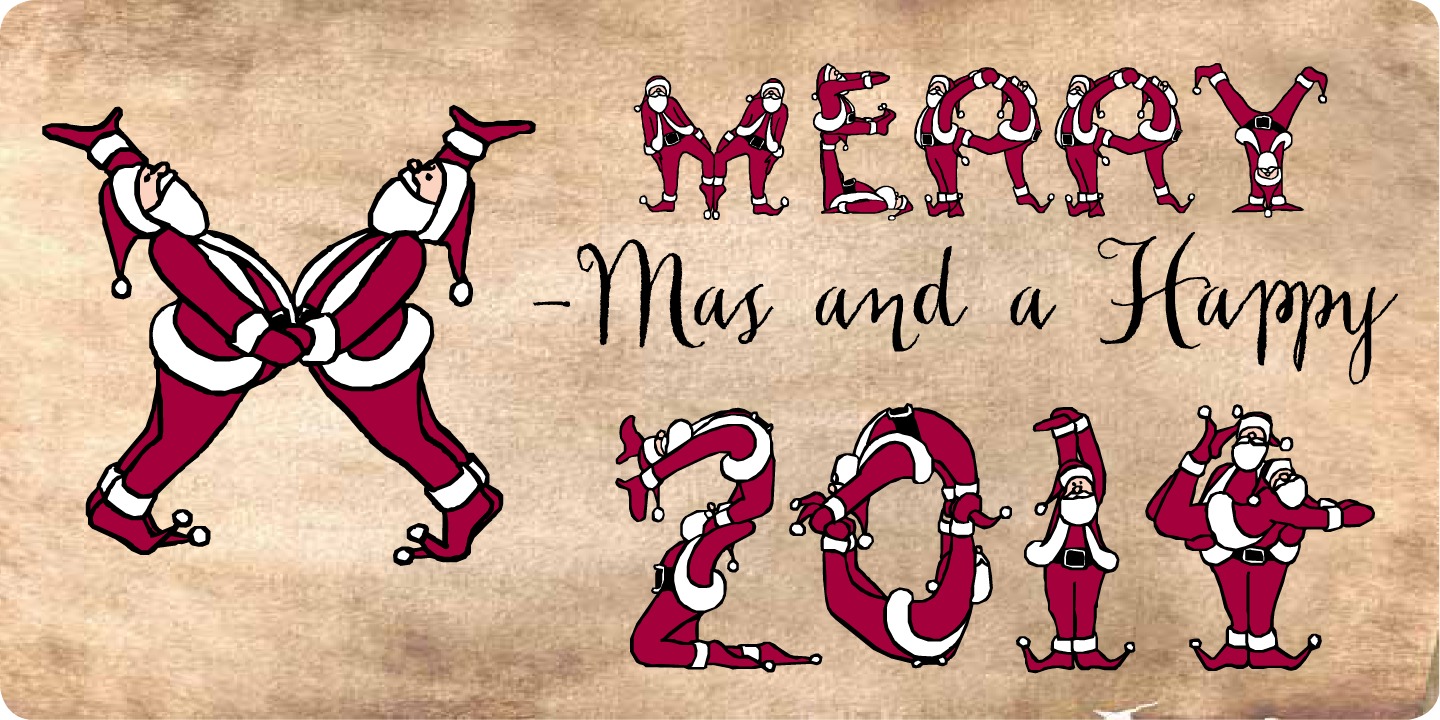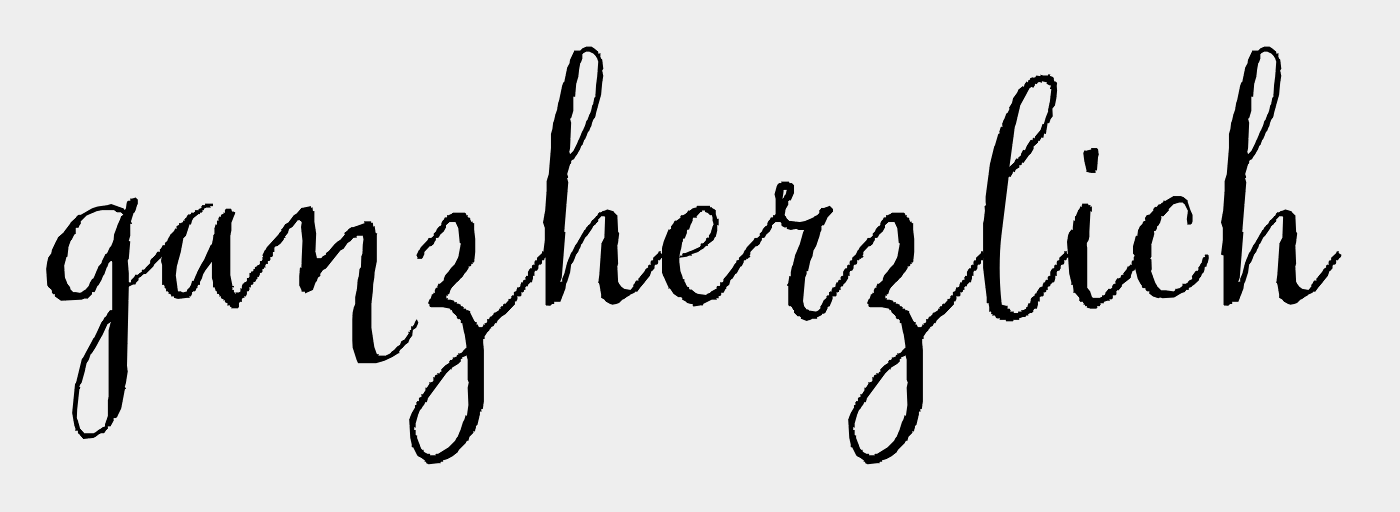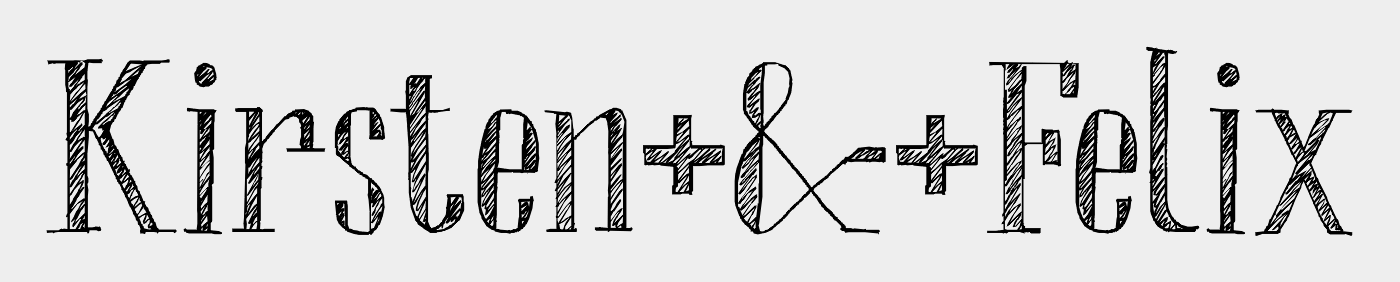
Schrift von Hochzeitseinladung gesucht
ich suche zwei Schriftarten, die ich auf einer Website für Hochzeitseinladungen gesehen habe.
Link zu einem Beispiel:
Kann mir jemand helfen?
Gerne auch eine ähnliche Schriftart, wenn die andere nicht identifiziert werden kann.
Schau Dir doch mal by MyFonts die Schriften von Laura Worthington und Emily Lime an. Das sind zwar nicht die von Dir gesuchten Schriften, aber sie haben ebenfalls viel Charme und sind formal dicht dran an der Schreibschrift.
wow, vielen Dank. Das ging schnell und hat perfekt geklappt. Ich hab nur bei der Santa's Pen Skin noch ein Darstellungsproblem. Hier werden mir auf myfonts.com keinerlei Großbuchstaben angezeigt - ist das bei euch auch so?
bei mir wird das hier angezeigt: gundw546.png
Ah ok, also kann ich mit Publisher nicht in dieser Schriftart schreiben? Hmm schade, das Programm ist nicht ganz so kompliziert und würde mir die Arbeit erleichtern :(
In Publisher 2013 bekomme ich meiner Meinung nach auch die korrekten Einstellungen angezeigt, allerdings sind diese ausgegraut:
Unter "Typografie" wären die Alternativen dann auswählbar, oder? Oh mann, jetzt hab ich das Teil vorschnell gekauft und kann nichts damit anfangen :|
In Word 2013 funktioniert die Schriftart grundsätzlich nicht, auch nicht mit Kleinbuchstaben :)
Dort habe ich aber immerhin die Einstellmöglichkeiten, bringt nur auch nichts
"Eine andere Schrift" wäre meine Empfehlung. Wurden ja schon viele hübsche ähnliche genannt.
Puh, scheint doch komplizierter zu sein als gedacht. Ich hab jetzt die Testversion von InDesign runtergeladen, finde aber auch keine Einstellung die mir die Großbuchstaben zulässt. Ich dachte das wäre bei "Glyphen" zu finden? Es geht bei mir eigentlich nur um Text ohne Grafiken oder Bilder, somit hätte Publisher locker gereicht. Jetzt schieße ich mit Kanonen auf Spatzen ;) Vielleicht guck ich mir die anderen oben genannten Schriften einfach nochmal an, wird einfacher sein als in InDesign einzuarbeiten
Schaut mal nach: Chameleon Pen.
Nachdem auch die Chameleon Sketch verwendet wird, ist die Chameleon Pen ebenfalls denkbar.
wow, ich habe gerade Chameleon Pen probiert und es scheint komischerweise identisch mit Santa's Pen zu sein. Habe jetzt jedenfalls exakt das Schriftbild des ursprünglichen Bildes mit Chameleon Pen und Publisher erhalten. Vielen Dank für eure Hilfe!!